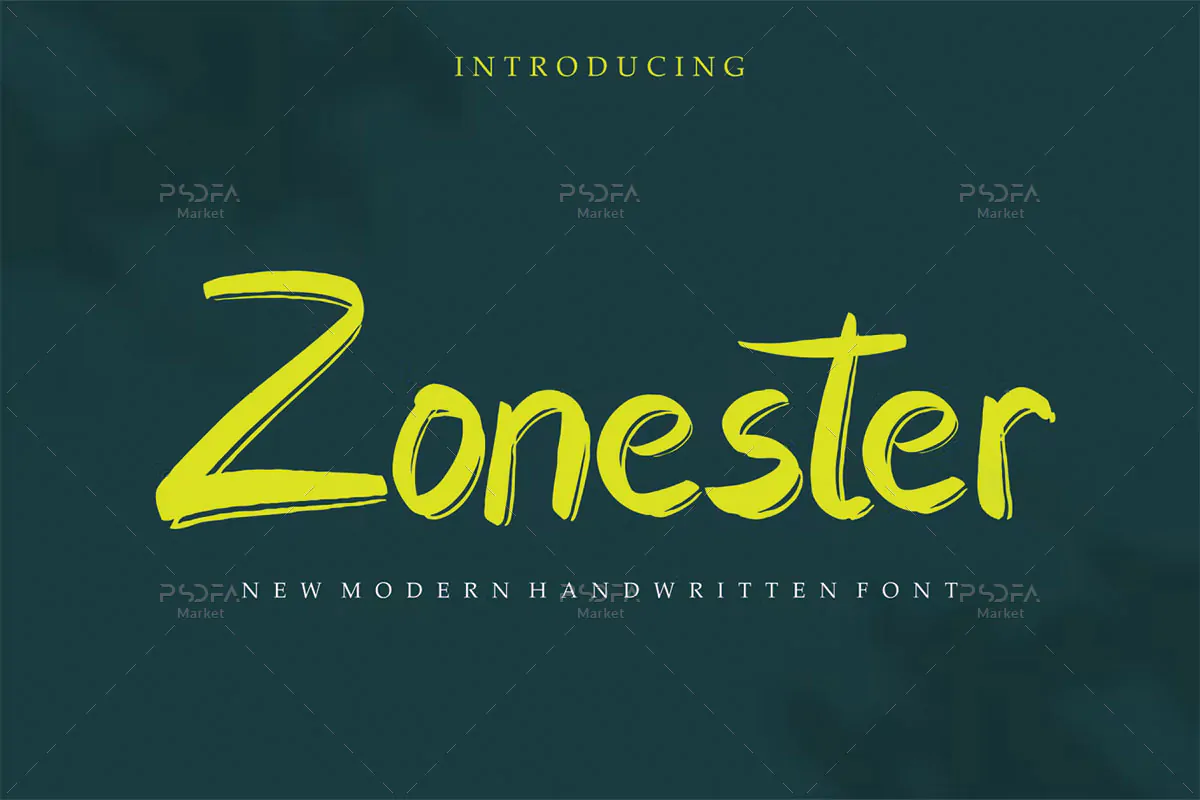
براش فونت انگلیسی Zonester
براش فونت انگلیسی
براش فونت انگلیسی Zonester یک اسکریپت فونت دستنویس است که مناسب جهت استفاده در طرح و پروژههای گرافیکی مختلف میباشد. فونت Zonester با وزن معمولی طراحی شده است که میتوانید از آن در طراحی پوستر، بروشور، کارت ویزیت، بسته بندی محصولات، تیشرت، ظروف یکبار مصرف، لوازم التحریر و … استفاده کنید.